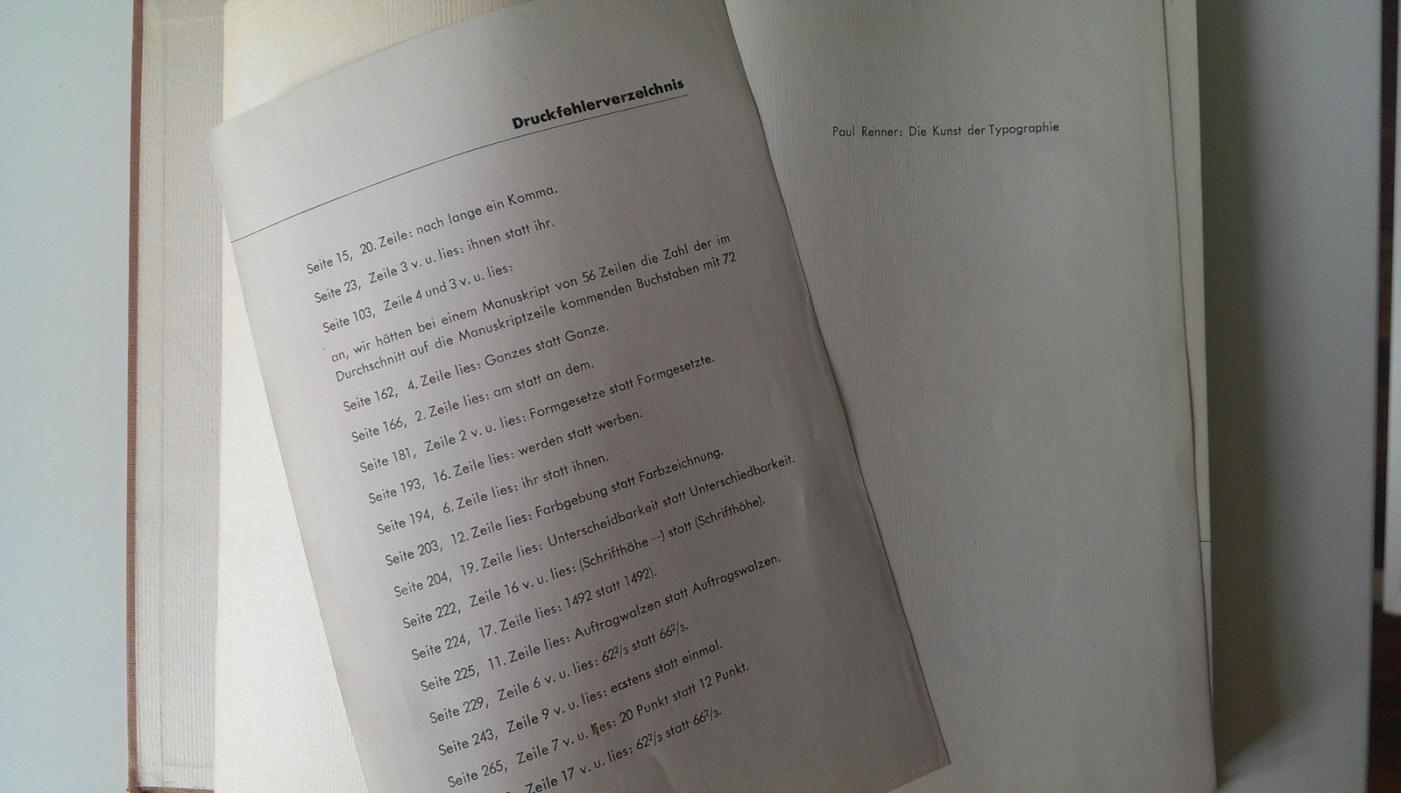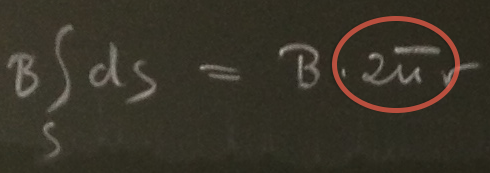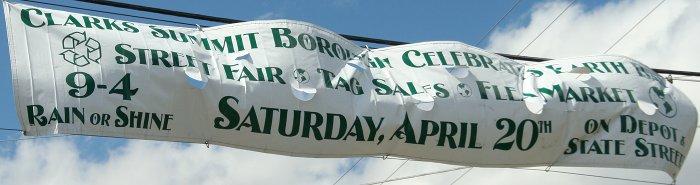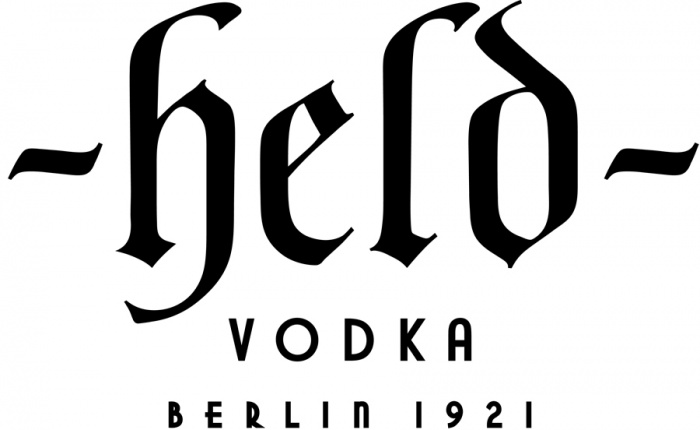
»Neue Berliner Papierkorbzeitung«: Ein Fall von Kunst und Humor!
Mein erster Eindruck: „Berliner Papierkorbzeitung: neues-deutschland.de
P.S. Ich habe dann doch mal auf den Link geklickt und war zumindest von der Webtypografie positiv überrascht. Webeingebundene Fonts im Mengentext funktionieren in so kleinen Graden selten so gut!
P.P.S. Es ist aber wieder mal sehr pöse von den Sozis, eine gebrochene Schrift für ein negativ konnotiertes Ulkblatt zu verwenden. Hier ein paar Streicheleinheiten für die Frakturliebhaber: :schonklar:
Soweit bin ich in der Tat nicht gekommen. :oops:
Tja, das soll wohl verdeutlichen, dass das ND besonders vorwärtsgerichtet progressiv ist. :-?
Mein Phyiskprof hat heute morgen spontan eine 2Ï€-Ligatur erfunden:
Das muss man wissen, ich habe ›zur‹ gelesen  :-)
Hätte ich auch, wenn ich nicht dabei gewesen wäre. Allerdings ist es schon verwunderlich, dass es so eine Ligatur noch nicht gibt. Schließlich schreibt man in den Naturwissenschaften ständig 2π …
Wenn man sich die Fehler anschaut, sind diese wohl großteils dem Setzer unterlaufen. ;-)
Welche Auflage ist das? 2. Auflage (1948)?
dummerweise ist der teil mit der auflage herausgeschnitten wurden, ich gehe aber davon aus das es die erste ist, denn vorn steht
"copyright 1939 by Frenzel & Engelbrecher" hinten: "Erstes bis fünftes Tausend. 1940"
Wo ist das denn her?
Aus dem Eltern Ratgeber Das gesunde Kind S. 19 (pdf mit 11 MB)
Das sieht man mal wieder, wie wichtig — sofern kein Versal-ß verfügbar ist — die Schreibung MASZ ist, die hier ja immer mal wieder in Frage gestellt wird.
Aus dem Eltern Ratgeber Das gesunde Kind S. 19 (pdf mit 11 MB)
Ah, danke für das Finden der Originalquelle!
Das sieht man mal wieder, wie wichtig — sofern kein Versal-ß verfügbar ist — die Schreibung MASZ ist, die hier ja immer mal wieder in Frage gestellt wird.
Ist halt auch nur die etwas bessere Notlösung unter den Notlösungen.
(KRAUSZ = Krauß oder Krausz?)
Dass die SZ-Schreibung heute nicht mehr alltagstauglich ist, hatten wir ja bei diesem Fall gesehen.
Ich weiß nicht, was das Beispiel belegen soll, außer, daß Marlies Kausch keine Ahnung hat und Bureaukratie nicht in der Lage ist, ihr das mitzuteilen. Was Krausz angeht: Gibt es diese Schreibvariante überhaupt?
Was Krausz angeht: Gibt es diese Schreibvariante überhaupt?
Na klar :-)
Ich weiß nicht, was das Beispiel belegen soll …
Dass die frühere Auflösung in SZ zunehmend nur noch von »Randgruppen« verstanden wird. (Bibliophile, Drucker, Designer, ältere Menschen) In der Architektur hat es sich auch bis heute erhalten (MASZSTAB), aber in der breiten Masse stößt es auf eben solche Ablehnungen. Da können die Conservativen noch so sehr mit der Historie wedeln. Es ist halt so. MASZ löst das gleiche Unverständnis aus wie CITAT und THÜR.
Was Krausz angeht: Gibt es diese Schreibvariante überhaupt?
Logisch. Es gibt Krauß/Krauss/Krausz, Keßler/Kessler/Keszler, Groß/Gross/Grosz usw. Alles gängige Eigennamen.
• »Slashed O« statt »slashed zero« :-o:-?
• Kapitälchen haben andere Form als Versalien (z.B. E in »CELEBRATES EARTH«, A in »SATURDAY, APRIL«).
• Schrift ist m.E. nicht wirklich geeignet für ein Banner, das oft durch den Wind verbeult wird.
• Wer kennt die Schrift? (Nur interessehalber, also reißt euch kein Bein aus!)
Wie bestellt man dieses Getränk?
Wenn der Kellner nicht zu einem kommt, an der Bar. ;-)